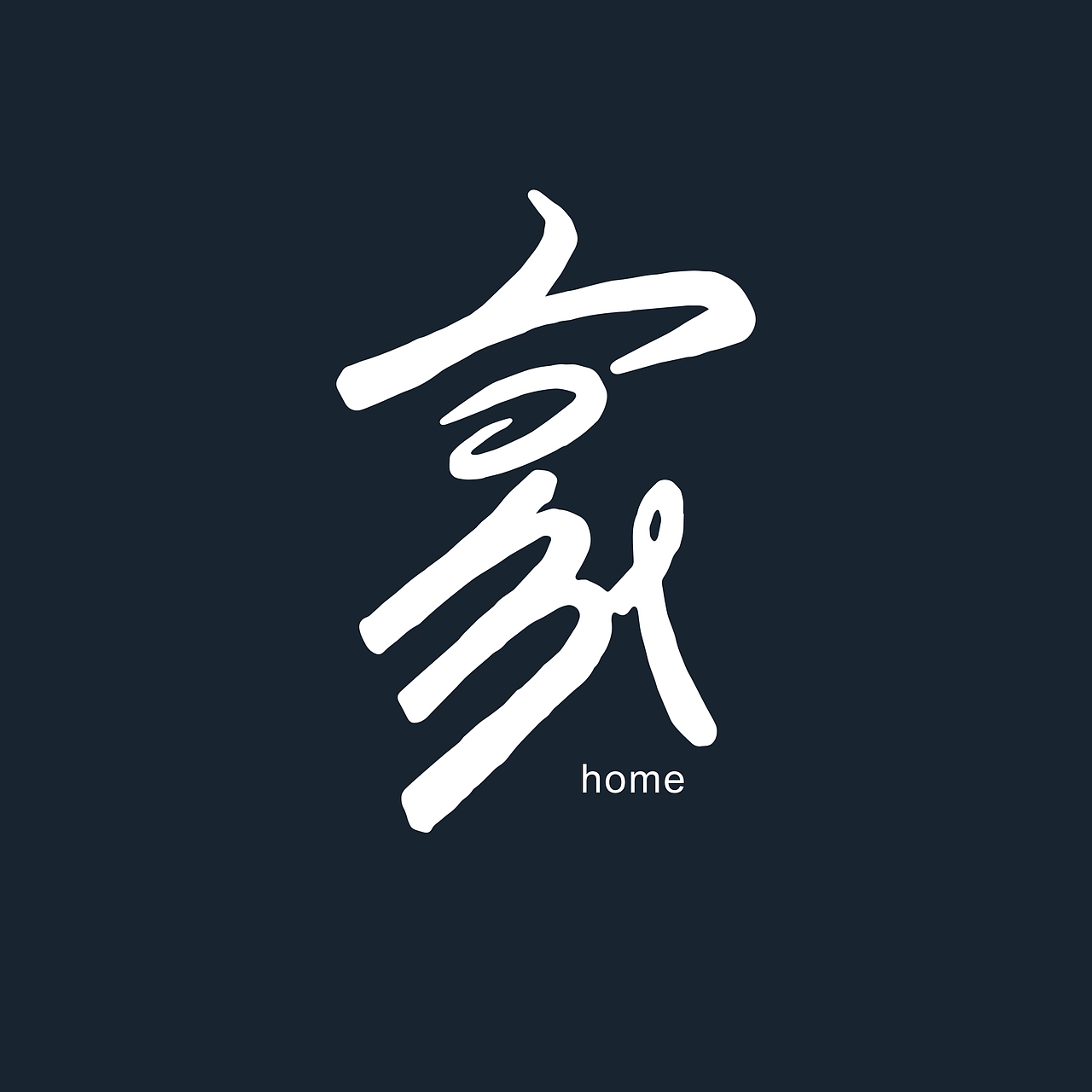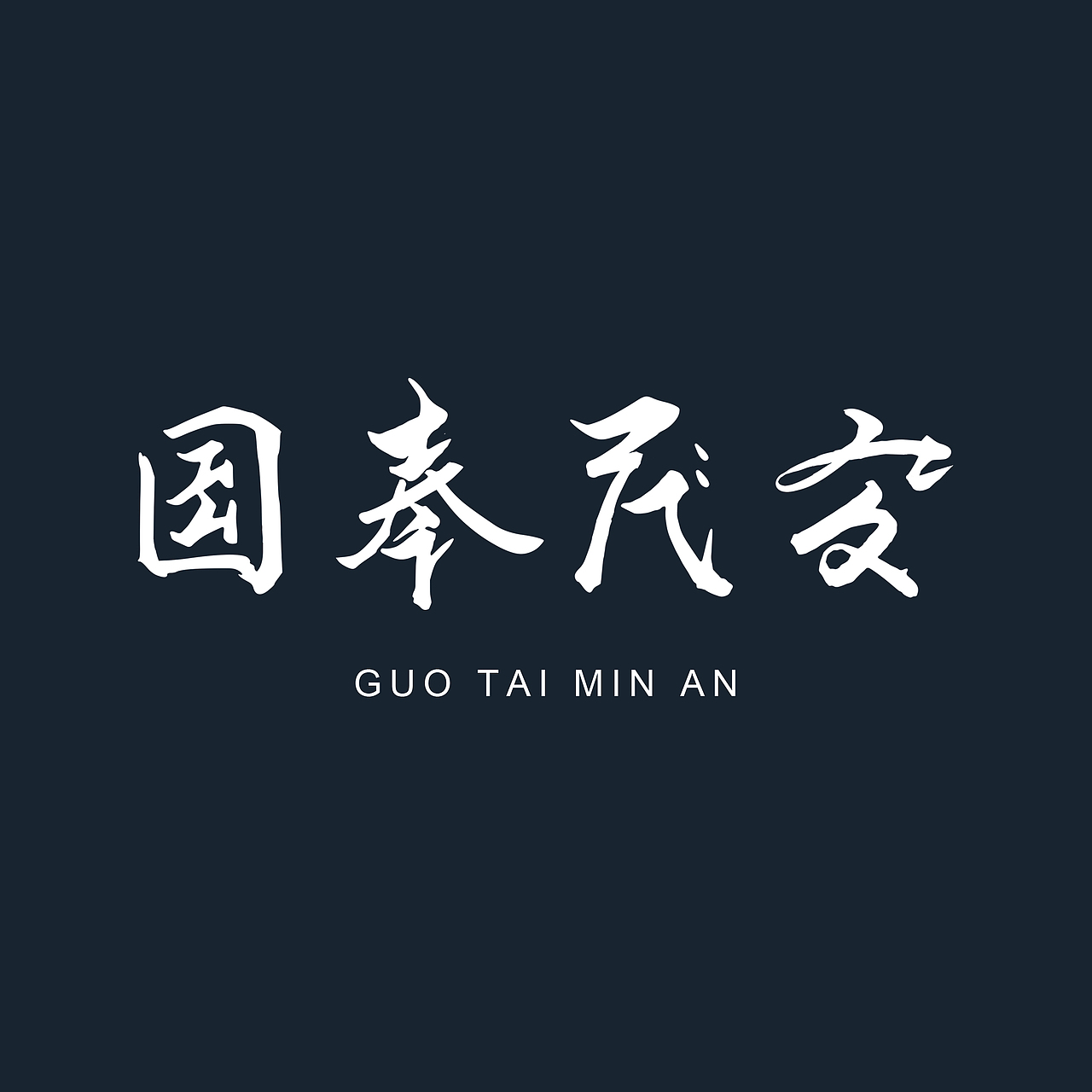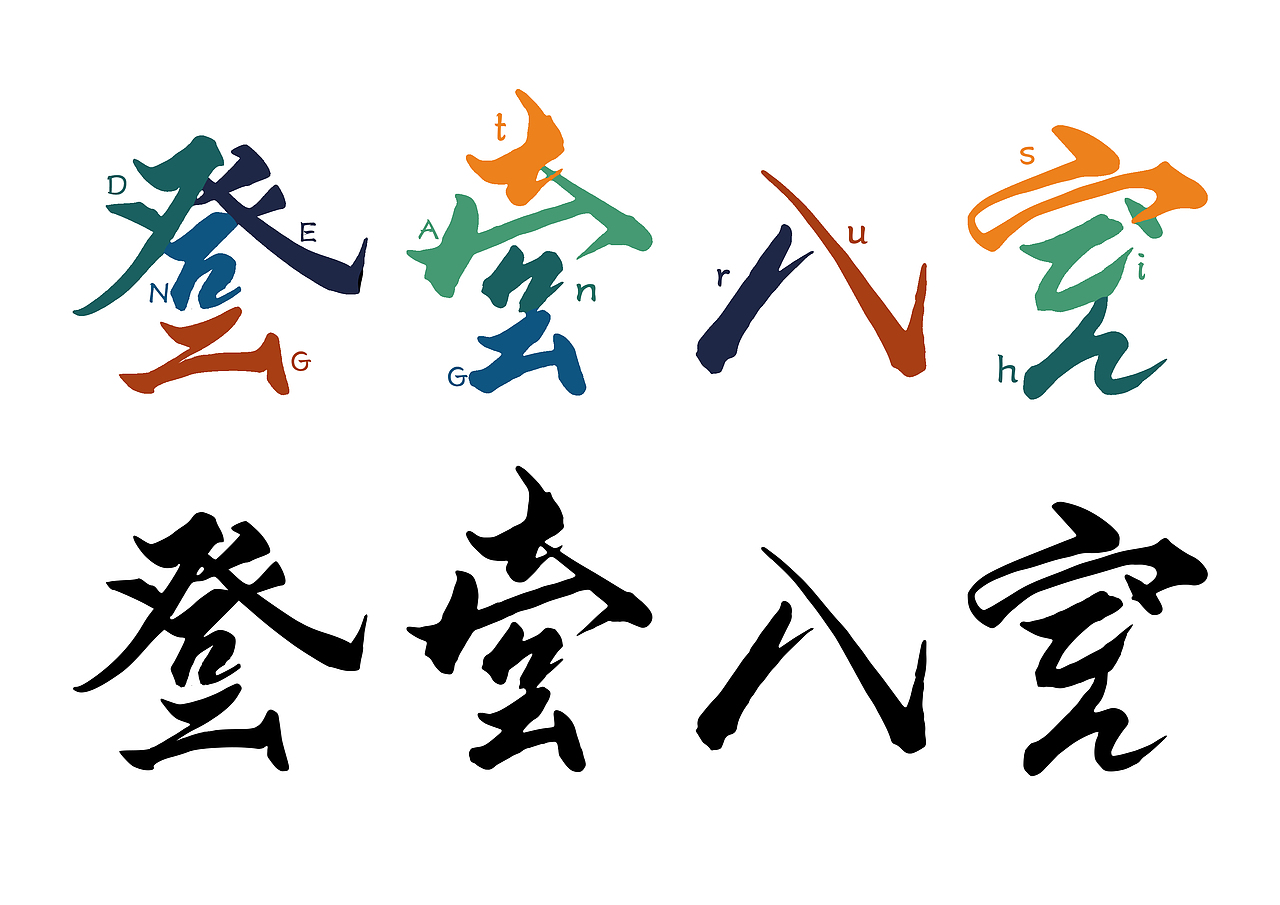
“家”系列 双语同意字体研究 第二期02工作室
“双语同意”字,中文西文的结合,体现国家与国家间、民族与民族间的文化交流与融合。此设计以“家”为主体,与其相对应西文单词“home”结合,体现“家”在横向上的交流性,纵向上的传承性。
“类双语同意”字,中文西文的结合,同样体现国家与国家间、民族与民族间的文化交流与融合。此设计以含有“宀”的成语为主体,分别从“个人修养”“国家形象”“宇宙探索”三方面进一步诠释“家”的深刻内涵。
此设计介于中文与英文翻译的差距性,从汉字拼音入手,同样中西文结合。